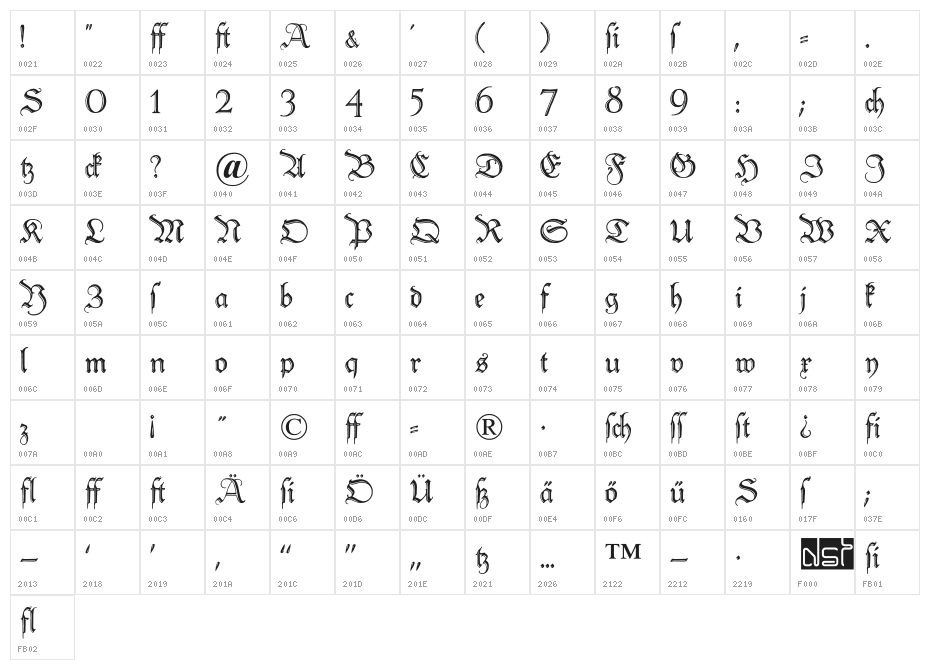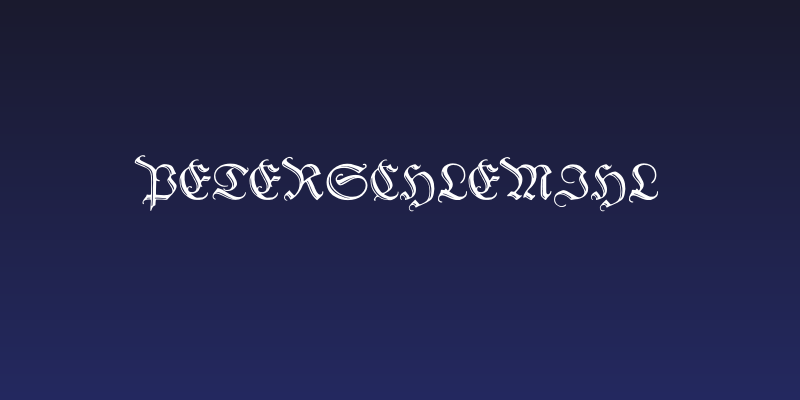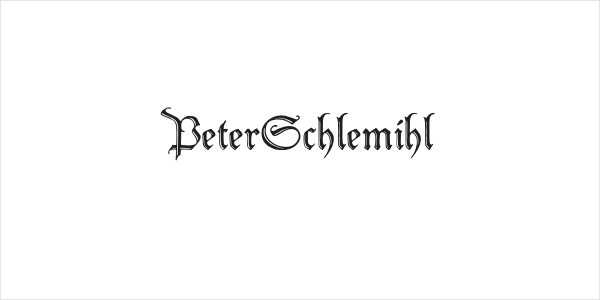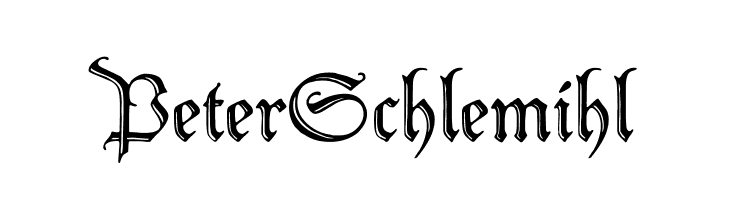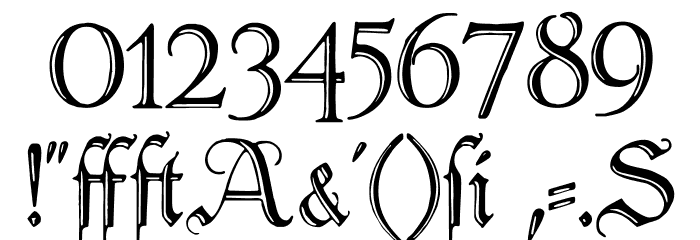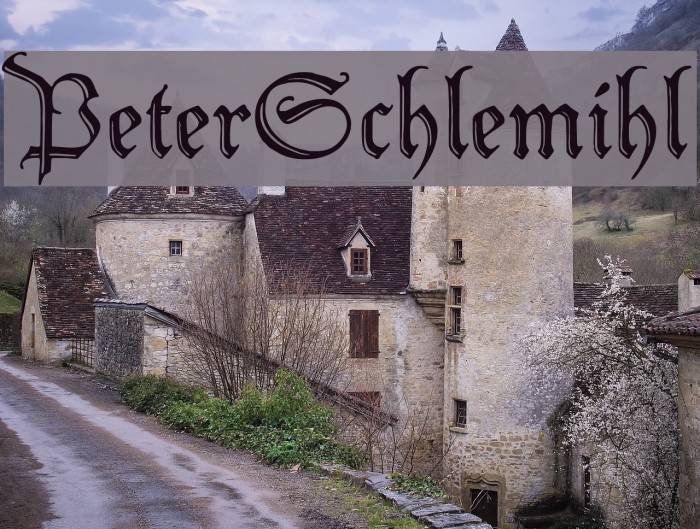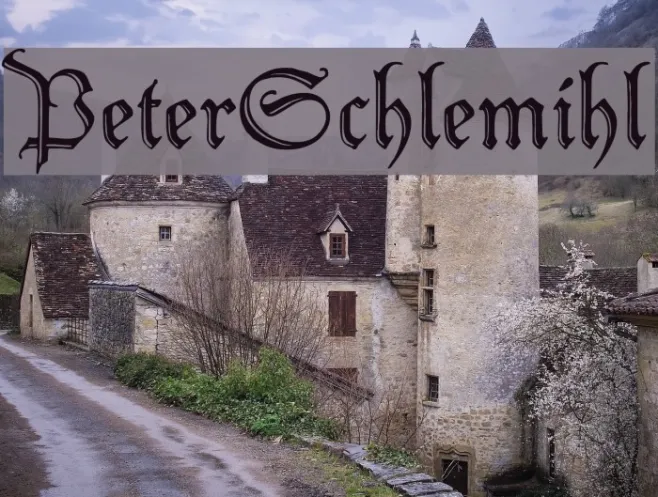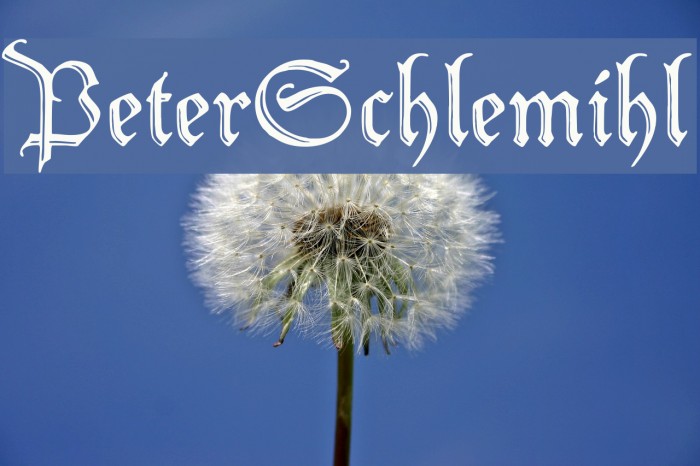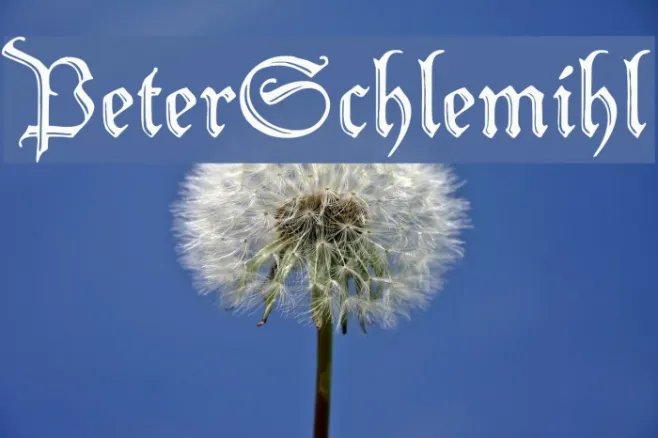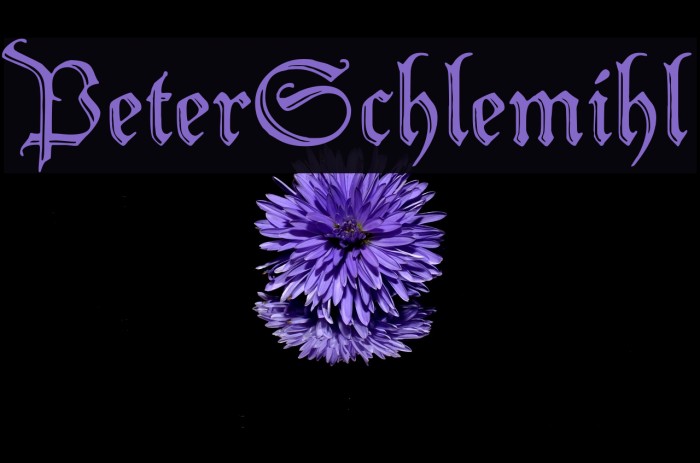
PeterSchlemihl Font
| Caso d'uso | Logos, Headlines, Decorative text |
| Progetti proposti | Ideal for projects requiring a historical or medieval theme, such as book covers, posters, or themed event invitations. |